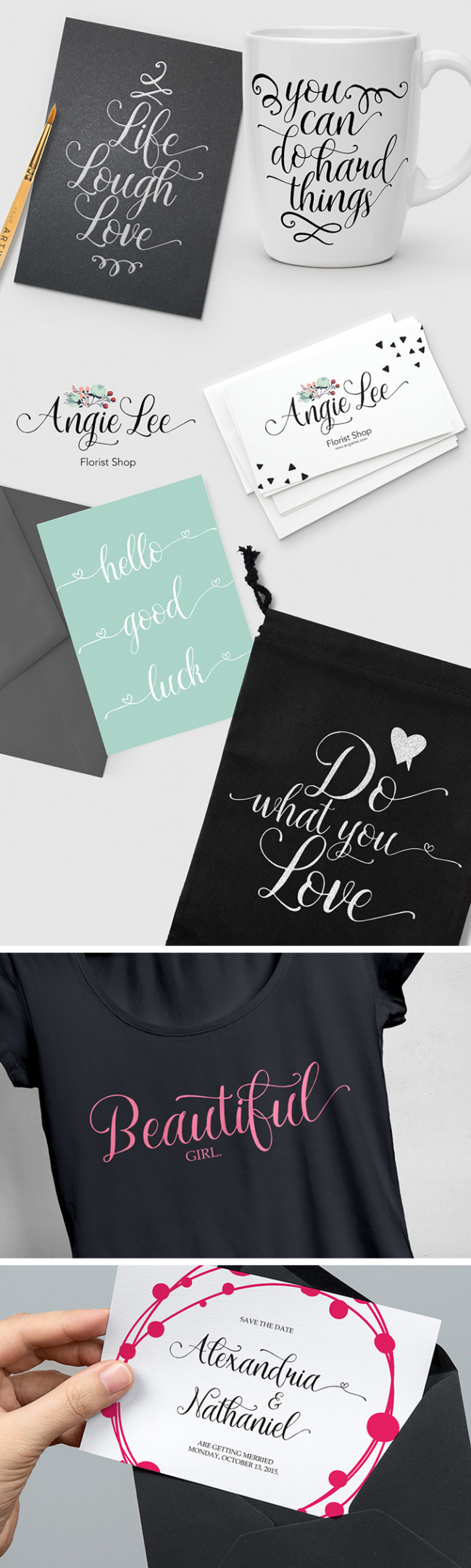
無料でダウンロードできるおしゃれな筆記体英字フォント Arabella Free Font
Arabella Free Fontは無料でダウンロードできるおしゃれな筆記体英字フォントです。
英字の筆記体は良いフォントを持っているだけで、デザインの幅が広がります。
ロゴやビジュアルなどのWebデザイン、パンフレットやマグカップ、サイン、名刺、Tシャツ、招待状、カードなどにも利用できます。